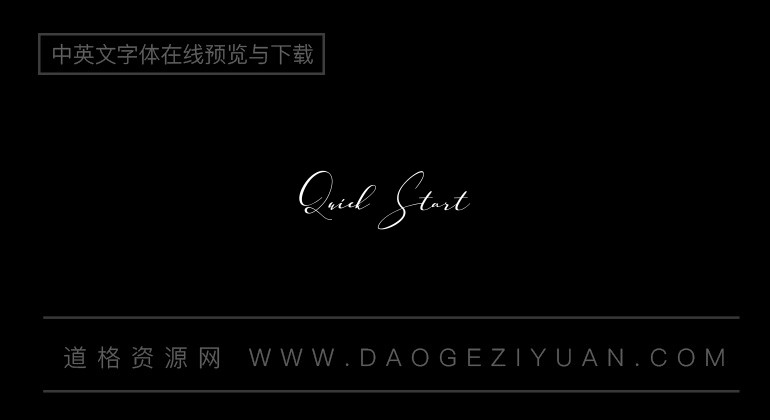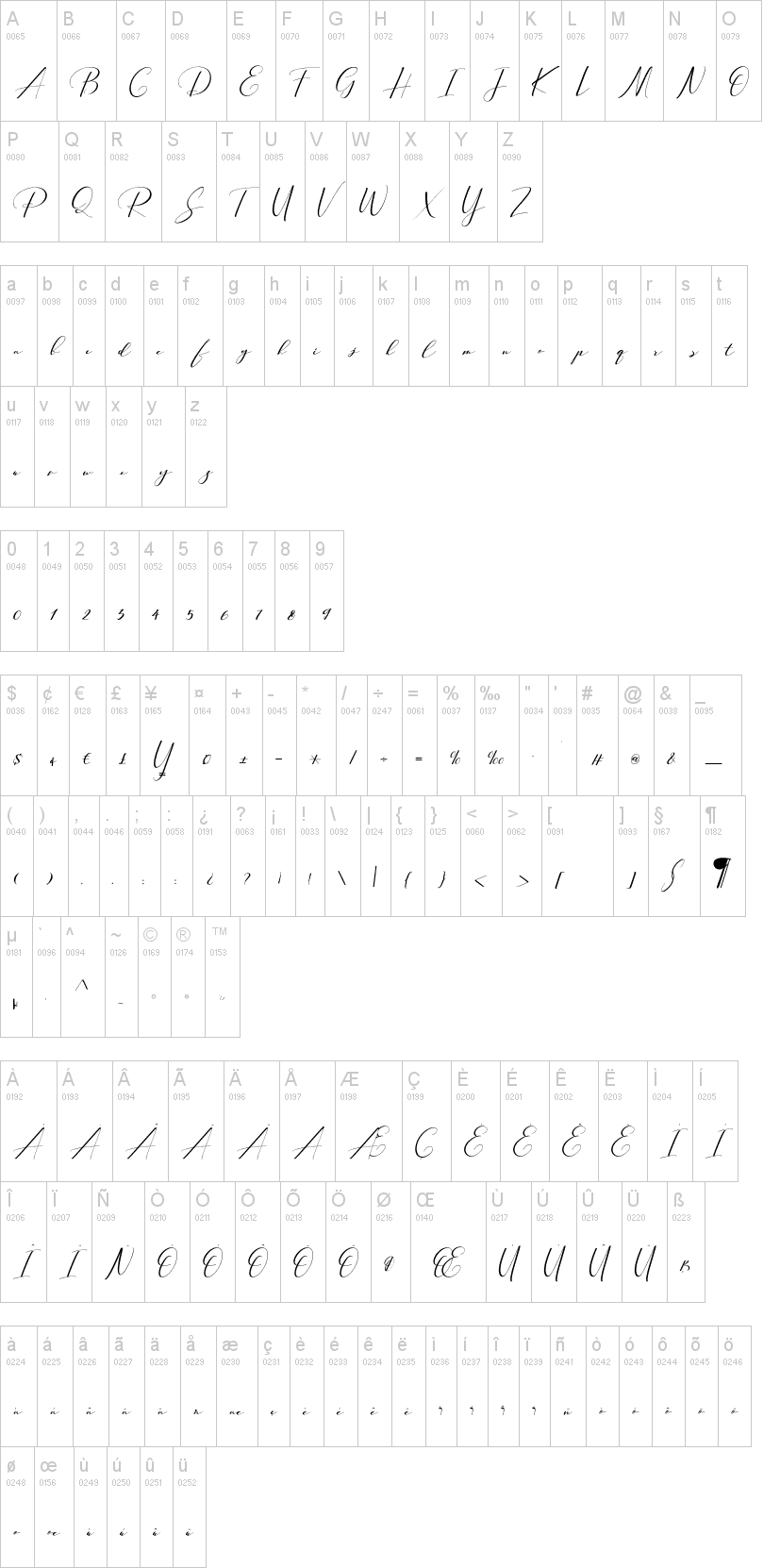
Quick Start字体是一款拥有简洁、现代风格的多功能字体,它有着非常优秀的设计,可以用于各种文档、在线和印刷媒体,特别适合用于标题、标签、报纸标题、广告等。它的特点是字体简洁大方,字形清晰,易于阅读,且易于记忆,可以提高文档的可读性。内容介绍
Quick Start是一款非常不错的手写艺术字体,具有很好的视觉感,适合于文化类的宣传设计、商业类品牌的广告和产品包装设计以及个性化文字排版等较多场景。